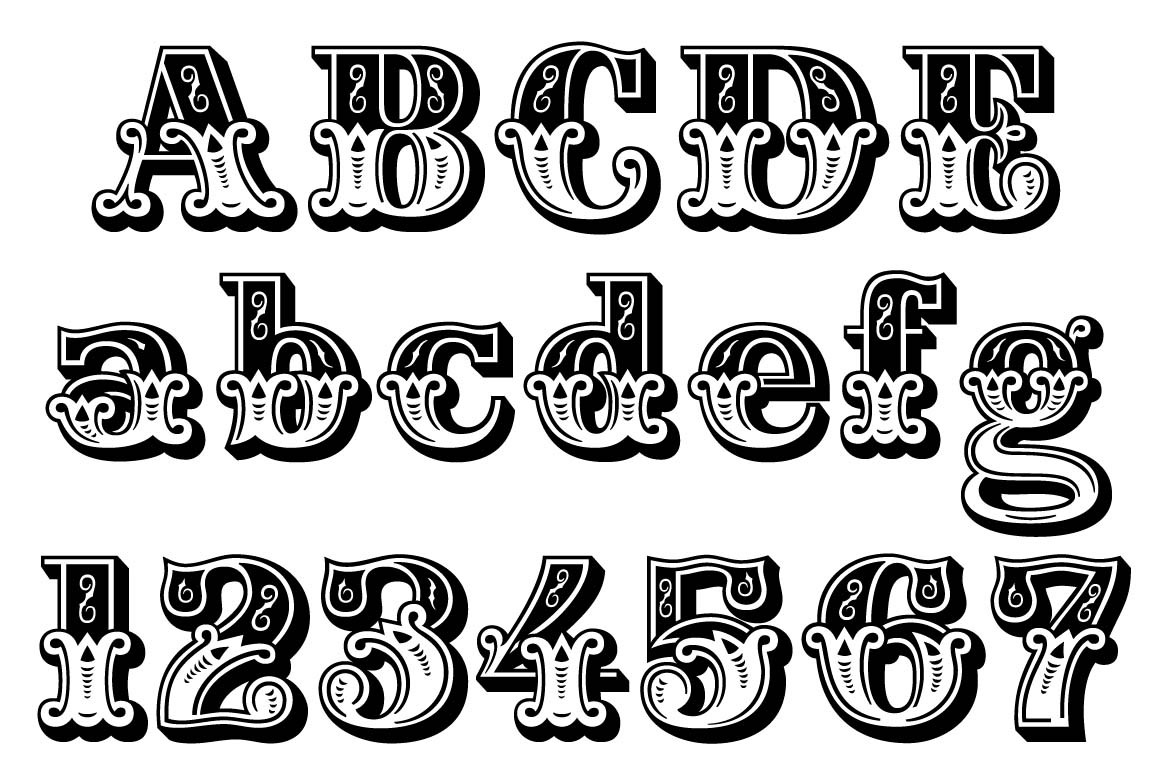
Лучшие бесплатные шрифты для дизайнеров 2020
Вы изо всех сил пытаетесь найти тот конкретный шрифт, который соответствует вашему творческому видению? Тогда вы попали в нужное место!
Эта коллекция сосредоточена на тех чистых и отличительных шрифтах, которые окажут профессиональное и очень разборчивое влияние на ваш дизайн, будь то в Интернете или в печати. Таким образом, не существует чрезмерно декоративных стилей, так как мы рассмотрели нарисованные от руки шрифты, научно-фантастические шрифты, короткие шрифты, готические шрифты, контурные шрифты, комические шрифты, граффити-шрифты и все остальные творческие и причудливые шрифты.
В данной статье мы попытались помочь вам быстрее найти идеальный шрифт, который вы искали.
Indulge
Indulge Script-это шрифт, адаптированный как для современного, так и для традиционного использования.
Source
Source Sans Pro включает варианты Regular, Italic, Bold, Semi Bold, Light, Black и Roman.
FV Almelo Rounded
FV Almelo Sans Serif включает только обычную версию. Создано Floris Voorveld.
Maven
Maven Sans Serif включает в себя варианты Light 100, Light 200 и Light 300. Разработано Джо Принсом.
Intro
Бесплатная версия Intro Sans Serif включает в себя обычные и встроенные варианты. Дизайн Мирослав Бекьяров.
Ostrich Sans
HK Grotesk Sans Serif включает в себя обычный, легкий, жирный и средний варианты. Разработано Hanken Design Co.
Qanelas
Qanelas Soft Sans Serif был разработан Радомиром Тиньковым.
Moderne
Moderne Sans включает в себя обычный и легкий варианты. Создано Мариусом Кемпкеном.
Blogger
Blogger Sans включает обычный, курсив, полужирный и полужирный курсив. Создано Сергеем Ткаченко.
Katahdin Round
Katahdin Round Sans Serif включает только обычную версию. Разработано Тайлер Финк.
Cast Iron
Cast Iron включает только обычную версию. Разработано Джереми Весси.
Relancer
Relancer Display включает в себя только обычную версию. Создано Райаном Молаг.
Overpass Webfont
Вдохновленный Highway Gothic, Overpass Sans Serif — это веб-шрифт, включающий варианты Light, Extra Light, Regular, Bold, Bold Italic и Italic. Создано Delve Fonts.
Fibon
Fibon Sans включает только обычную версию. Разработано Валерио Делл’Эдера.
Corduroy
Шрифт Corduroy отлично смотрится на обложках, плакатах, открытках. Создано Райаном Уэлчем.
Promesh Athletic
Promesh — это бесплатный шрифт для надписей, разработанный с использованием проблемных сеток, схожий с теми, которые использовались в школьных баскетбольных формах из прошлых лет. Включает в себя обычные и стежка вариантов. Разработано Полом Рейсом.
Lunchbox Slab
LunchBox Slab — это уникально нарисованная от руки гарнитура, которая дает множество настраиваемых опций и полностью аутентичный внешний вид.
Zenzero Grotesk
Свежий, эксцентричный и стильный дисплейный шрифт, наполненный смесью без засечек и плит. Разработано Валерио Делл’Эдера
Chunk
Chunk — это очень жирный шрифт с засечками, вдохновленный старыми американскими газетными заголовками в западном стиле. Создано Лиги Подвижного Типа.
Choplin
Aleo
Aleo — современный бесплатный шрифт, который был создан как компаньон slab serif к семейству шрифтов Lato. Включает полужирный, полужирный курсив, обычный, обычный курсив, легкий и легкий курсив. Создано Алессио Лайсо.
Twentytwelve
Шрифт Twentytwelve представлен в трех вариантах: обычный, жирный и тонкий.
Разработано Домом Катапано.
Airbag Uppercase
Airbag — это современный шрифт с засечками. Только включает заглавные буквы. Разработано Саймоном Стратфордом.
Lumberjack
Включает в себя обычные, грубые, встроенные и теневые варианты. Дизайн Алексей Калинин.
Ansley
Ansley — это шрифт Slab Serif, вдохновленный ретро-дизайном. Включает варианты Bold, Inline, Light, Black, Outline и Regular. Создано Кади Йеско.
Korneuburg
Korneuburg Slab включает в себя варианты Bold, Light и Regular. Создано Flö Rastbichler.
Baron Geometrical
Baron Sans Serif включает в себя обычный, жирный и черный варианты. Разработано Фрэнком Хеммеканом.
Exo Geometric
Exo Sans Serif включает обычный, курсив, полужирный, полужирный курсив, светлый, светлый курсив, черный, черный курсив, дополнительный жирный, дополнительный жирный курсив, дополнительный легкий, сверхлегкий курсив, средний курсив, полужирный, полужирный курсив, тонкий и Тонкий курсив Дизайн Натанаэль Гама.
The Metropolis
Metropolis Typeface — это современная геометрическая гарнитура с открытым исходным кодом.
Norwester
Norwester Sans Serif включает только обычную версию. Создано Джейми Уилсон.
Сделать жирный шрифт в Инстаграме – это хороший способ выделиться и привлечь внимание к своему профилю. Украсить им можно пост, шапку страницы или другие элементы. Сама социальная сеть не предлагает инструментов для красивого оформления текста, но эту задачу можно выполнить другими способами.
30. Heisman
Heisman — это шрифт с заглавными буквами и уникальными маленькими и большими буквами. Шрифт идеально подходит для использования в проектах, связанных со спортом, особенно в заголовках, майках, брендинге, плакатах, упаковке и рекламе. Шрифт геометрически идеален, а значит, эстетичен для глаз.